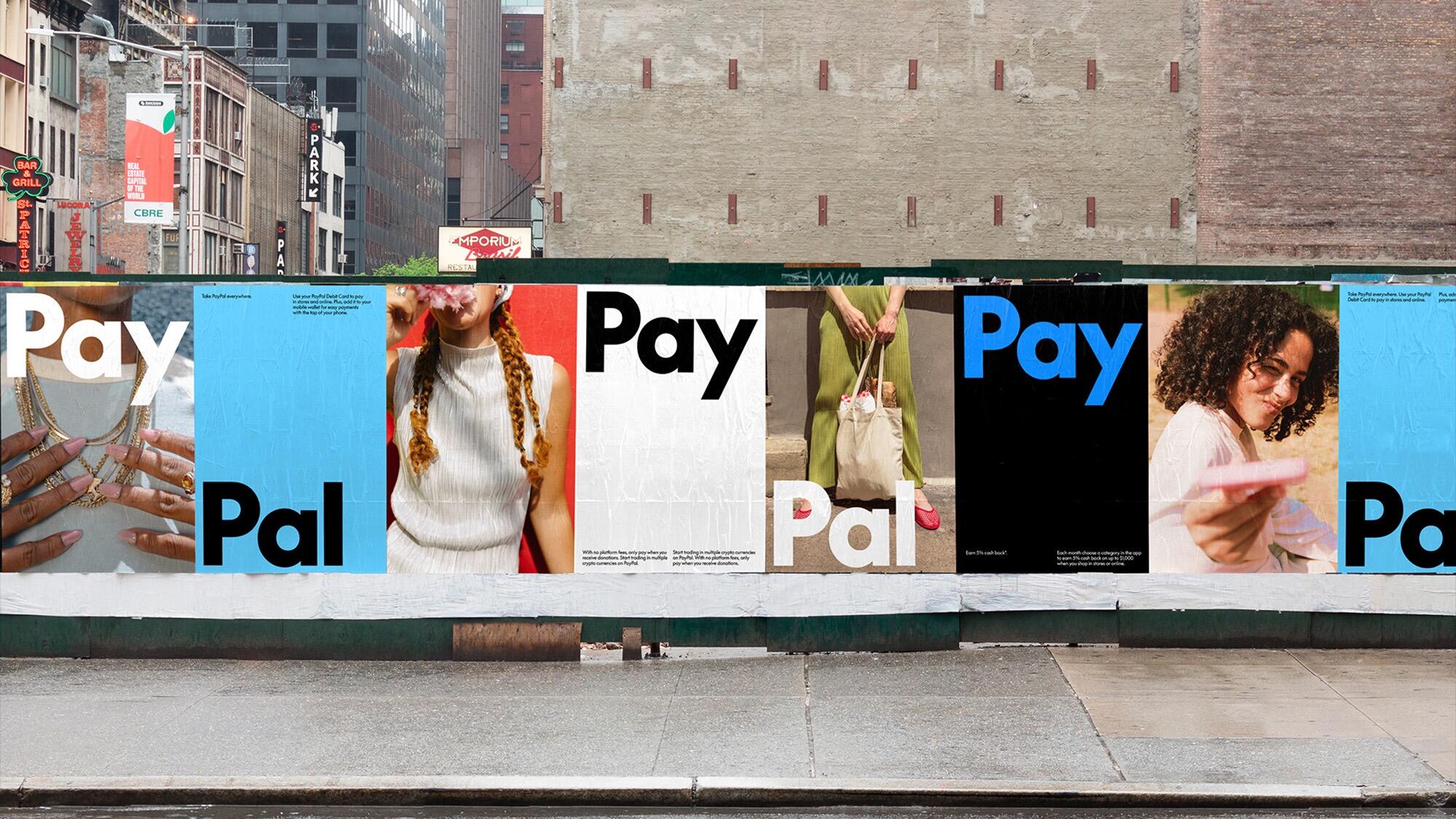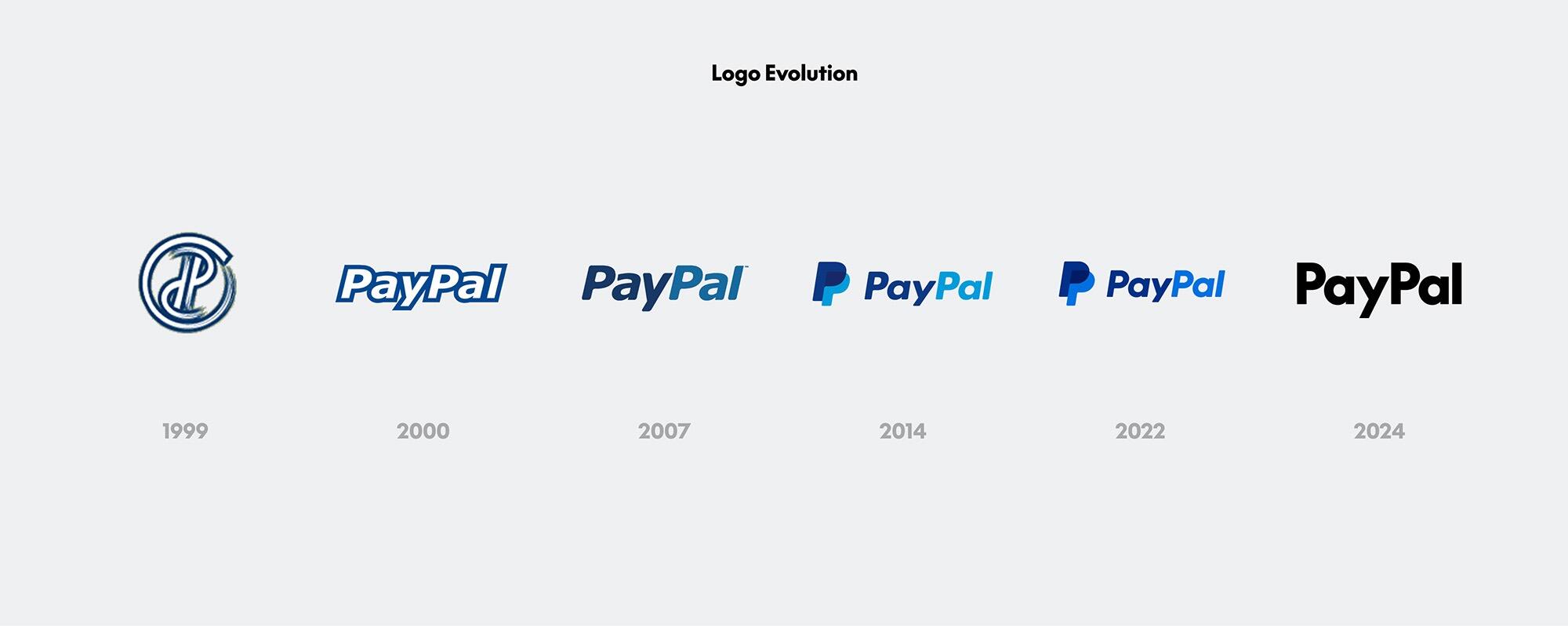
Neues PayPal-Design von Pentagram
Aber schön wie sie
– von "timeless type" schreiben,
– bei einer Schrift die "Futura" heißt,
– und die dann doch noch ein "contemporary redrawing" braucht
Ich frage mich ob man das einer anderen Agentur überhaupt abgekauft hätte. 🤐
Die Kunst besteht halt nicht in der Gestaltung, sondern in der Marketing-Lyrik … bei der Lektüre wird mir körperlich unwohl.
Und was ist, wenn man bei diesem Manipuliere nicht mehr mitmachen will?
Ich finde, es entbehrt nicht einer gewissen Ironie, dass mittlerweile nicht nur die Endverbraucher, sondern auch die Auftraggeber eine gehörige Portion smoke and mirrors abbekommen.
Wenn man das unschön findet, muss man sich dem entziehen – und etwas anderes machen. Dieser Hokuspokus ist inzwischen Industriestandard, das wird sich so bald nicht ändern, fürchte ich.
Mich stört am meisten, dass die Bildmarke und die Wortmarke nicht mehr zusammenpassen ...
Saat und Ernte? 😬😳🙄 Dem folgend wären Agenturen, die das betreiben dann die nächsten. 🤐
Dafür sorgt dann eine KI.
Mich auch. Da ist vieles handwerklich eher unterdurchschnittlich, dafür aber wortreich (rich in words) verpackt. Und mit Sicherheit teuer bezahlt.
*) oder auch nur rich wie in that's rich.
Ich frage mich ob das alles genauso von der Agentur kommt oder ob bestimmte Entscheidungen im Prozess vom Kunden diktiert wurden. Das Festhalten an der kursiven Bildmarke beispielsweise ...
Wie es normalerweise läuft:
Agenturen werden zum Pitch eingeladen.
Die siegreiche Agentur macht sich an die Arbeit und liefert eine ziemlich saubere und schlüssige Arbeit ab.
Im Lauf des Prozesses wird durch Ahnungslosigkeit des Auftraggebers und persönliche Einflussnahme von "Entscheidern" seitens der Auftraggeber die Qualität von 100 % auf 50 % gedrückt.
Der übrig gebliebene Rest muss der Öffentlichkeit irgendwie so verkauft werden, dass es nach einem schlüssigen Konzept aussieht. Da lässt sich Logorrhoe nicht vermeiden. Die Herleitungen und Erläuterungen zum neuen Design werden ja immer erst nach Abschluss des Designprozesses verfasst, um sich die Mängel schönzureden.
:-) in einer idealen Agentur ...
In einer realen Agentur gibt's auch unterschiedliche Prioritäten zwischen den Akteuren ...
Ich mags. Die Stärken des neuen Erscheinungsbildes liegen meines Erachtens in den digitalen Anwendungen und Mikro-Animationen. Da merkt man schnell, dass Andrea Trabucco-Campos seine Erfahrungen aus der Zeit bei DesignStudio und Gretel hat einfließen lassen. Über die etwas uninspirierten Plakate, Taschen etc. kann ich da hinweg sehen, da PayPal ohnehin zu 99 Prozent im digitalen Umfeld stattfindet (zumindest meiner persönlichen Wahrnehmung nach).
Nichtsdestotrotz bin ich kein großer Fan der Supreme, bei der mir die Ober- und Unterlängen zu raumgreifend sind (analog zum Futura-Vorbild).
Deswegen "ziemlich" :-D. Der Qualitätsverlust findet aber meiner Erfahrung nach immer nach der ersten Präsentation statt.
Manchmal aber auch der Realitätsbezug, wenn das Luftschloss auf die (bisher nicht kommunizierten, aber natürlich existierenden) Anforderungen trifft ...
Auch das, ja. Wobei eine Agentur die Anforderungen zum Großteil hätte abschätzen können müssen, wenn sie sich intensiv mit dem Kunden auseinandergesetzt hätte. Und man kann als Agentur ja proaktive Dinge abfragen, auch wenn sie nicht gebrieft wurden.
Da habe ich schon schlimmeres Marketing-Sprech gehört ... auch bei Kollegen und Abschlusspräsentationen an Hochschulen ;-)
Was genau meinst du mit Mikro-Animationen? :shock: